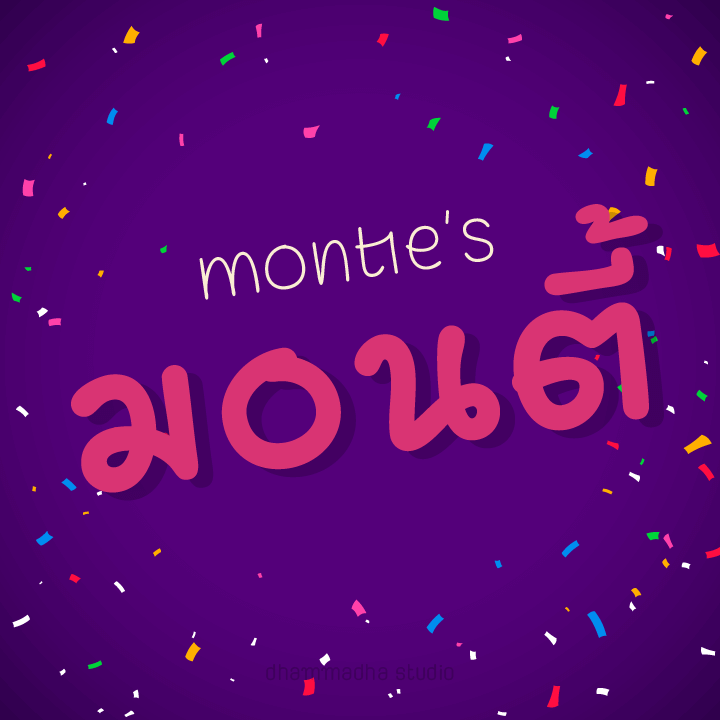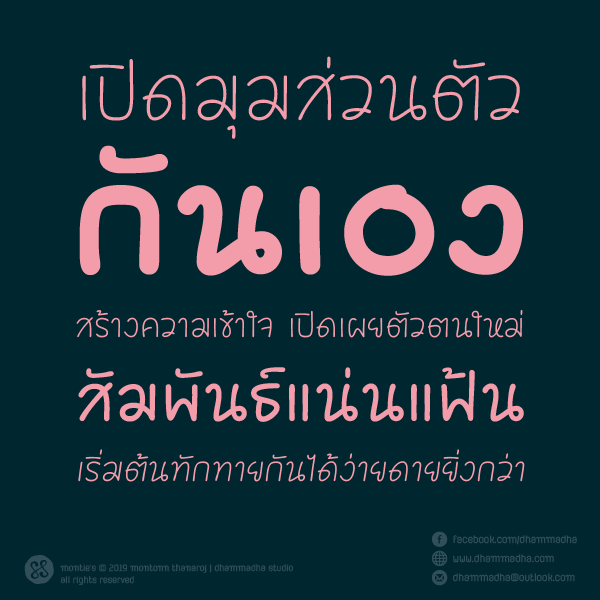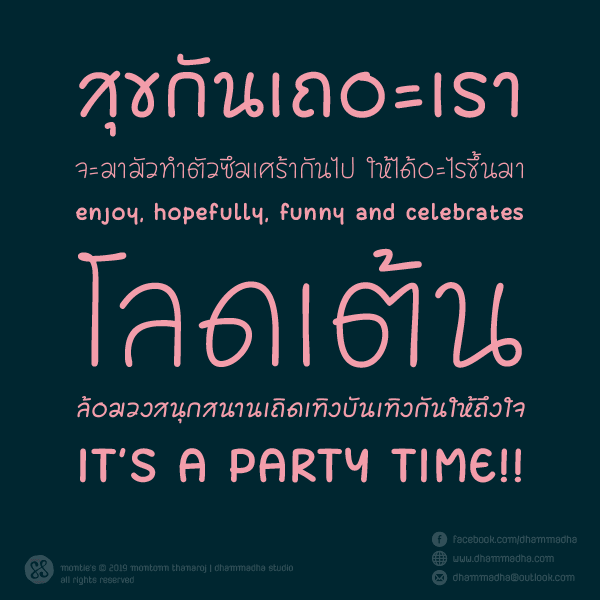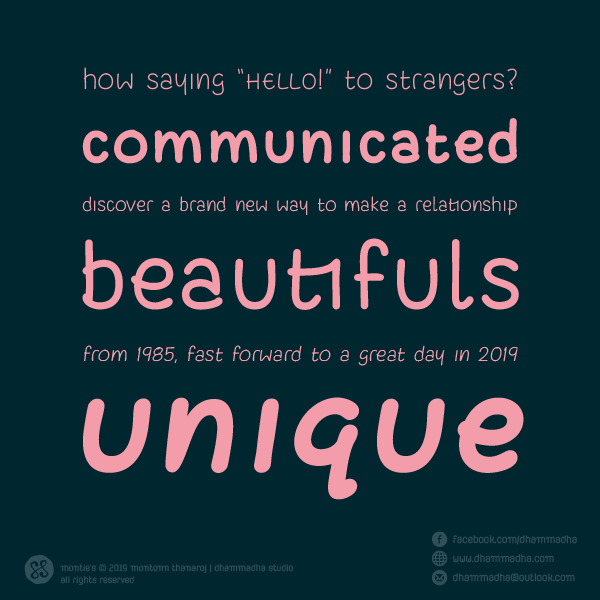
มอนตี้ | montie’s
เข้ามาเสริมทัพชุดฟอนต์ลายมือที่เคยเปิดให้ใช้งานมาก่อนหน้านี้ ที่มาที่ไปของแบบใกล้เคียงกัน แต่ปรับเปลี่ยนรูปลักษณ์การนำเสนอให้แตกต่างออกไปจากเดิม
โดยชุดฟอนต์ “มอนตี้” ประกอบด้วยฟอนต์ 3 น้ำหนัก รวมทั้งสิ้น 6 ไฟล์ฟอนต์
- light
- regular
- bold